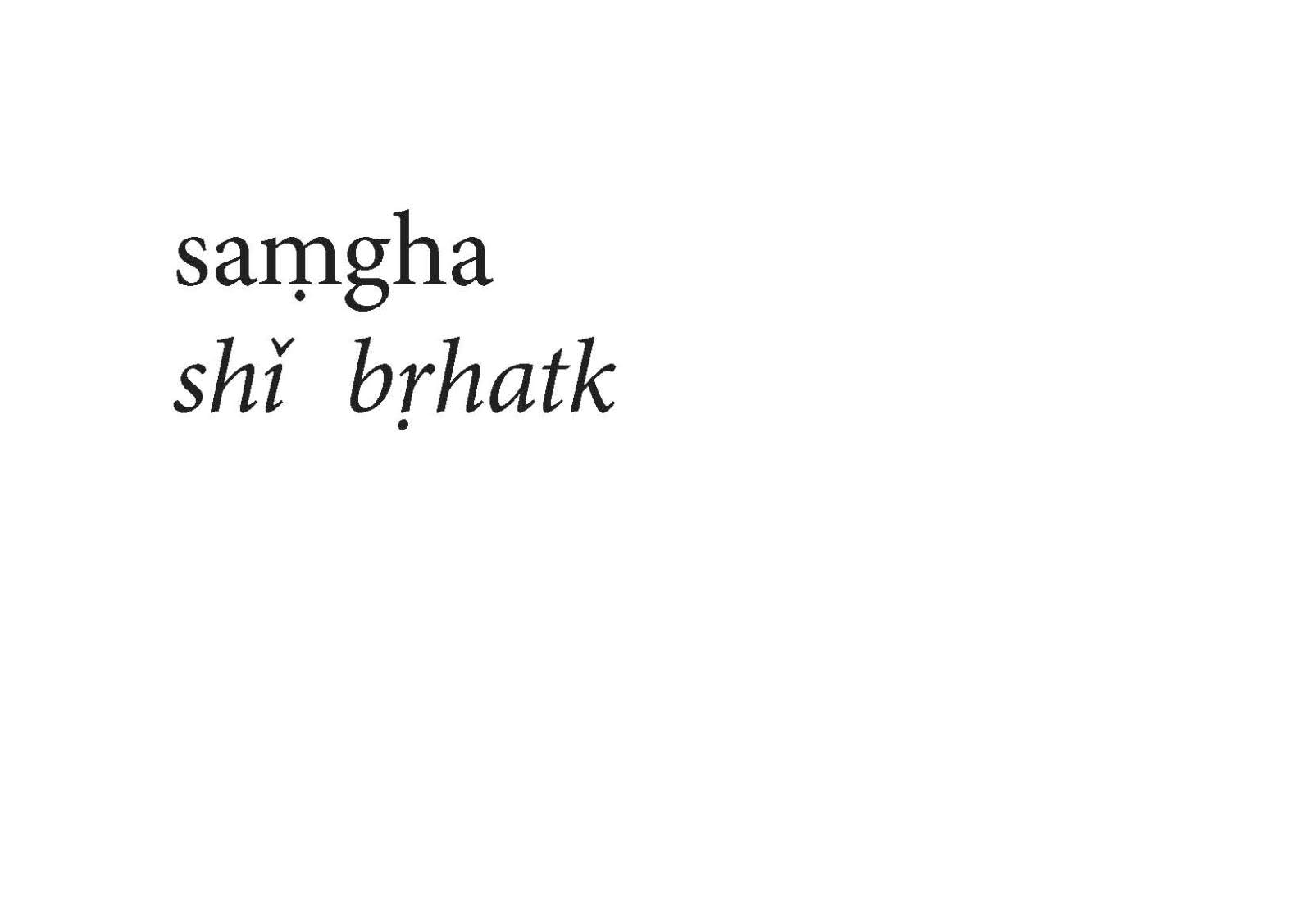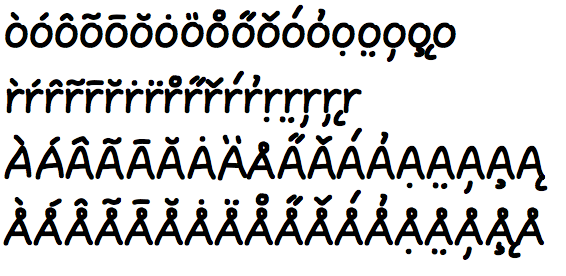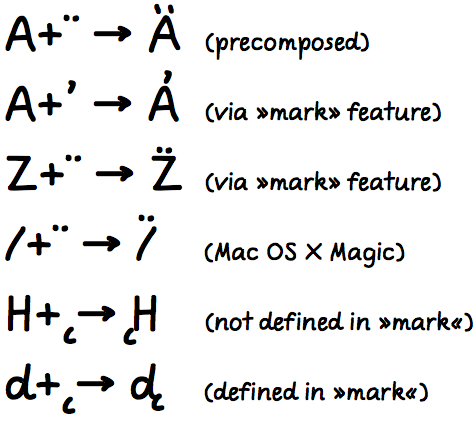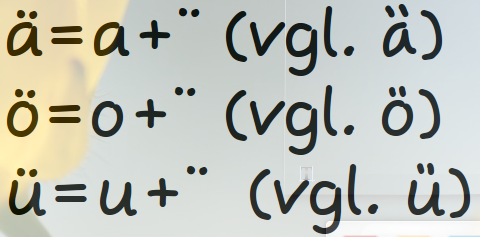
Ich korrigiere gerade einen Sammelband, in dem es u.a. einen Artikel über Buddhismus in China gibt. Bei der Transliteration einiger Originaltexte werden Zeichen wie m, n, r und t mit Punkt darunter oder i mit nach oben geöffnetem Häkchen gebraucht (ich habe leider keine Ahnung, wie die Dinger korrekt heißen). Der Setzer des Verlages hat offenbar die Worddatei des Autors in InDesign importiert, festgestellt, dass es diese Zeichen in der Minion, aus der das Buch gesetzt ist, nicht "fertig" gibt und die Zeichen aus der Times genommen. An einigen Stellen fällt das auch nur bei genauem Hinsehen auf, an anderen Stellen stört es aber (zumal sich der Setzer nicht sehr viel Mühe gegeben hat, Größe und Neigung der Zeichen anzupassen).
Ich habe nun zu Hause herumprobiert und die nötigen Zeichen "gebastelt" (siehe Bild). Die Methode "i-Punkt per Grundlinienversatz absenken und durch extremes Kerning nach links unter den Buchstaben schieben" kommt mir aber ein wenig dilettantisch vor. Deshalb meine Frage: Gibt es eine "professionellere" Methode, diese Zeichen in der Minion hinzubekommen? Spricht etwas dagegen, die Zeichen überhaupt aus der Minion zu nehmen (wenn sie dort nicht "fertig" vorliegen), hat der Setzer also möglicherweise das einzig Vernünftige getan (und muss jetzt nur noch ein bisschen Detailarbeit leisten)?
Und wo ich einmal beim Fragen bin: Einer der Autoren möchte drei ohne Leerzeichen gesetzte Bindestriche in den Text einbauen, um zu signalisieren, dass mehrer Sätze aus einem Zitat ausgelassen wurden. Ich habe so etwas noch nie gesehen ... aber das muss ja nichts heißen ...
Hier kommt eine Antwort von einem Unbedarften in Fremdsprachen-Typografie. Diese Glyphen scheinen in einem mir unbekannten Schriftsystem vorzukommen, die aber bei reichhaltigen Unicodeschriften belegt sind. Z.B. Lucida Grande kennt »Latin Small Letter M With Dot Below« unter der Unicodebelegung U+1E43 (Glyph ID: 1669), die anderen Glyphen ebenso. Die Minion scheint all diese nicht an Bord zu haben.
Hier findest Du einen Artikel und Downloadhinweise für ein kleines Script das solche Kombinationen in Indesign erzeugt. Die Minion verfügt nämlich sowohl über den tiefgestellten Punkt als auch über das Hatschek und ein kleines i ohne Punkt - damit lassen sich die Zeichen dann erzeugen. Ist suboptimal, aber allemal besser als die Times :wink:
Und eine Auslassung kennzeichnet man eigentlich so: [...]. :D
Da gibt es wirklich nur 3 Möglichkeiten:
- fehlende vorgefertigte Zeichen aus einer fremden Schrift nehmen (verhältnismäßig einfach, aber mit Störfaktoren)
- fehlende Zeichen aus dem Grundbuchstaben und dem "solo"-diakritischen Zeichen (das sind die Häkchen, Punkte, ...) über manuelles Kerning zusammenbauen (etwas komplizierter, ließe sich aber auch mit Indesign über Kontext-Formatierungen halb-automatisieren)
- Eine Schrift nehmen, die diese Zeichen schon vorgefertigt besitzt (je nachdem ist die Auswahl recht begrenzt, ich könnte mir vorstellen, dass die freie Schrift Gentium das aber beherrscht).
Beste Lösung (Theorie):
hoffen, dass sich die combining diacritic marks mal durchsetzen ... Hier würden die gewünschten Zeichen automatisch aus Grundbuchstaben und Diakritika zusammengesetzt (also Lösungsansatz Nr. 2, automatisiert). Dass das gut aussieht, darum muss sich dann der Schriftgstalter kümmern, nicht mehr der Setzer. Die Schriften würden wesentlich schlanker und übersichtlicher werden (kein Wust an vorgefertigten Zeichen mehr), aber gleichzeitig universeller einsetzbar.
Frage: gibt's inzwischen Programme, die das ccmp-Feature unterstützen?
es gibt meiner meinung nach nur eine vernünftige lösung des problems, nämlich: eine schrift zu verwenden, die – von hause aus oder nach bearbeitung – die erforderlichen zeichen an der richtigen stelle enthält. alles andere kann dir mit einem falschen klick um die ohren ?iegen.
was die lizenz der minion erlaubt, weiß ich nicht. daher hier eine kleine auswahl von schriften, in denen du zeichen wie ?, ?, ?, ? oder ? bereits ?ndest:
alright sans
andron
apex new
calibri
cambria
charis SIL
dejavu sans/serif
gentium
linux libertine
segoe UI
An der Schriftwahl ist nichts mehr zu ändern. Das Buch ist schon gesetzt. Und der Verlag wird von seiner Hausschrift nicht abweichen (obwohl ich mich wundere, warum Brill die Minion gewählt hat, wo der Verlag doch viele Bücher im Themenumfeld Sinologie, Buddhismus etc. im Programm hat und schon öfter auf das Problem der fehlenden Zeichen gestoßen sein muss).
Ich freue mich ja, dass ich mit meiner "Bastelarbeit" gar nicht so falsch gelegen habe (und das richtige Zeichen für den Punkt finde ich noch ...). Auf jeden Fall werde ich den Setzer bitten, alle Buchstaben aus dem Vorrat der Minion zusammenzustellen (auch wenn das etwas mühsam ist, vielleicht lässt er sich ja auf das Script ein).
Beste Lösung (Theorie):
hoffen, dass sich die combining diacritic marks mal durchsetzen ...
Frage: gibt's inzwischen Programme, die das ccmp-Feature unterstützen?
z ?? ? ? z?
Du nimmst das falsche ¨ (U+00A8 ). Du brauchst U+0308 (combining diaeresis).
Jetzt geht’s :rockon:
Zu der Frage mit den Bindestrichen als Auslassungszeichen: Für ausgelassene Sätze kann man Halbgeviertstriche oder Geviertstriche verwenden, aber keine Bindestriche!
Falsch: Erster Satz. --- Fünfter Satz.
Richtig: Erster Satz. ––– Fünfter Satz.
Auch richtig: Erster Satz. ——— Fünfter Satz.
Die Striche sollten einen kleinen Abstand haben und sich nicht berühren.